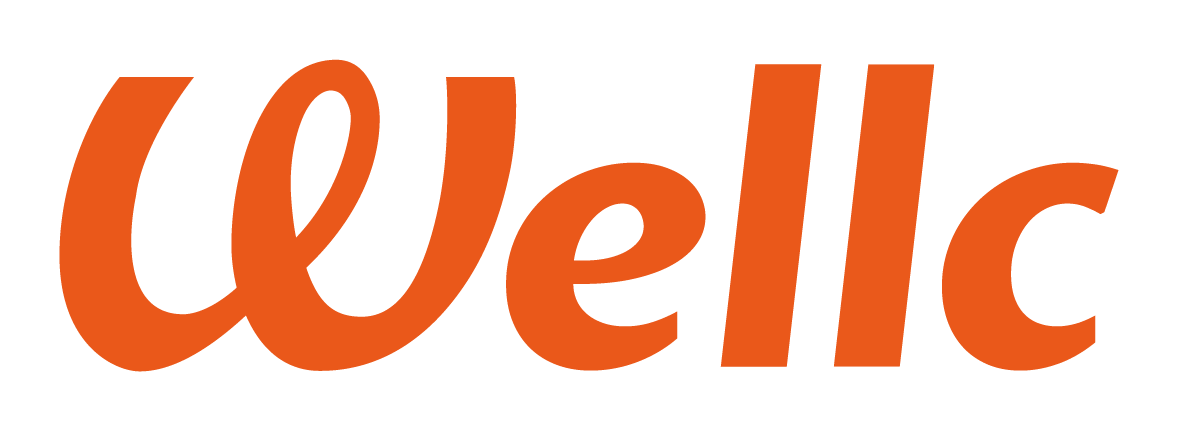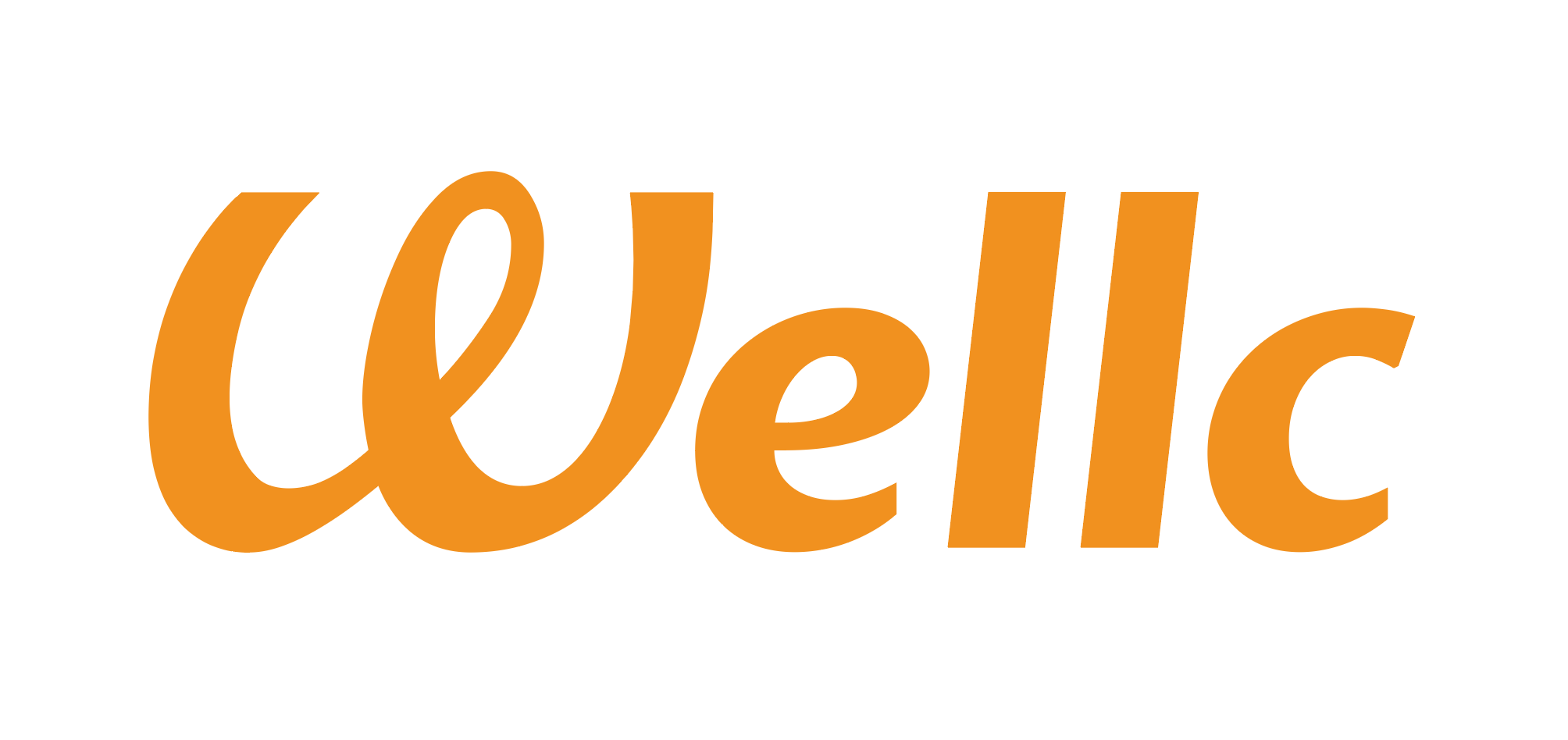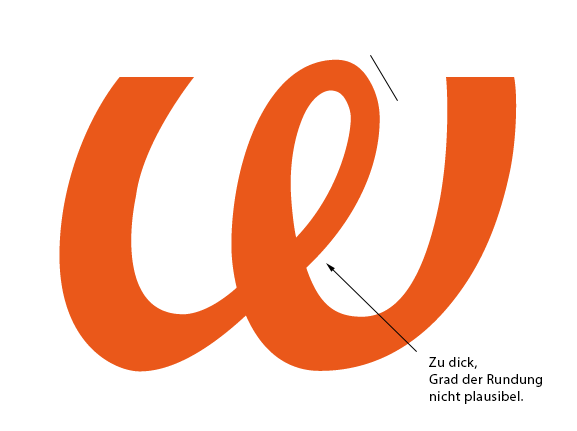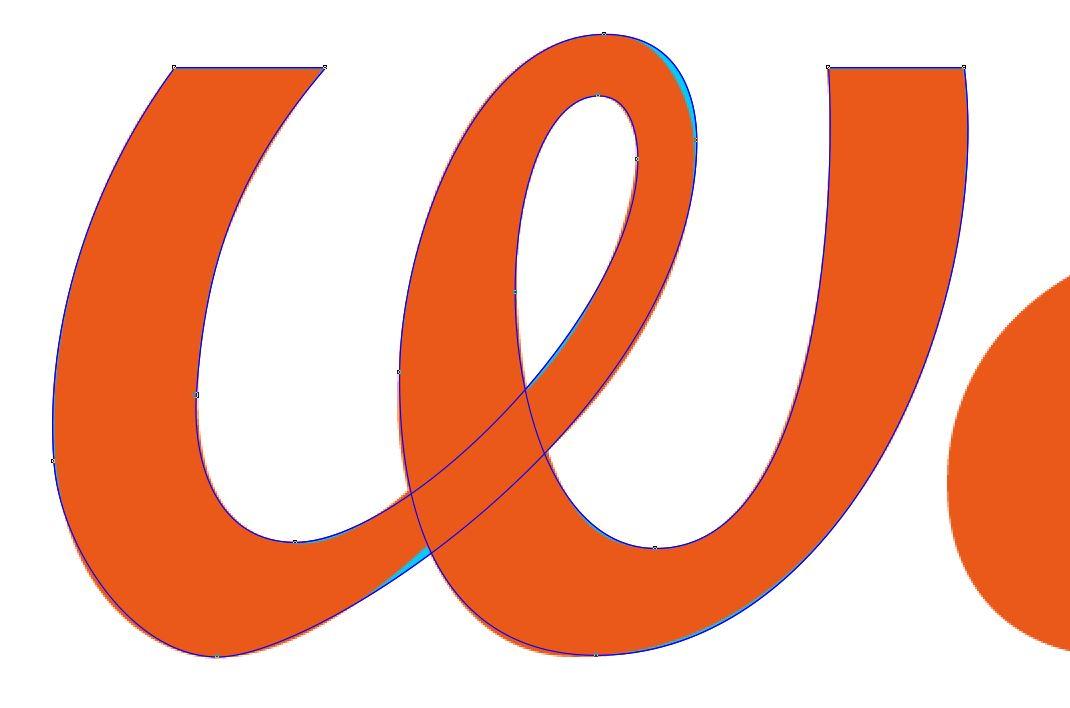
Schriftgestaltungsversuch: W mit Schlaufe
nachdem ich keine passende Schrift gefunden habe, die ein W mit Schlaufe im Glyphenset hat, habe ich einfach eins gezeichnet.
Ich mache das eigentlich ungern, weil ich weiß wie anspruchsvoll und anstrengend es sein kann, ein Buchstabe neu zu zeichnen. Da ich aber gerne diese Fähigkeit beherrschen würde, versuche ich es einfach.
Ich bitte um Kritik.
Sieht noch nicht nach natürlicher Führung des Schreibwerkzeugs aus. Grundschlecht sieht es auch nicht aus. Aber eben noch nicht so ganz schlüssig. Mein Eindruck geht aber nicht weit über das Gefühl, das da noch nicht alles stimmt, hinaus. Ich würde mir das mangels kalligraphischer Erfahrung selbst gar nicht zutrauen.
Ist immer noch nicht so ganz stimmig. Die Schlaufe sieht oben rechts abgeflacht aus. Und ich bilde mir ein, dass die Kreuzung noch korrekturbedürftig ist. Solange du daran arbeitest, dürfen sich die Outlines an der Kreuzung überlappen.